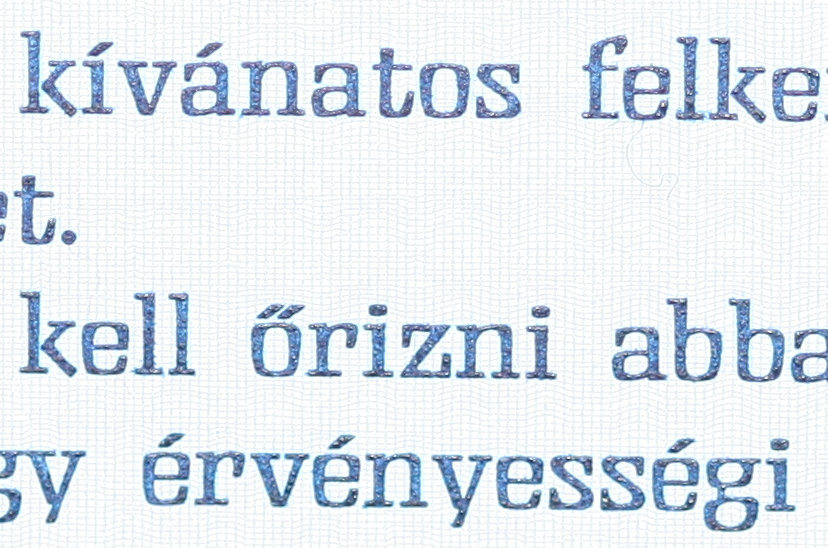
Ich hatte wegen des Hungarumlaut-Problems mal einen Bug-Report eingereicht – und Bruno Maag und Mark Shuttleworth haben beide geantwortet. Ich fühle mich ja so geehrt! :party:
Das Problem, dass die beiden kollidieren, wenn sie den selben, flachen Winkel haben wie der einfache acute, ist vermutlich jedem bekannt, der die Zeichen schon mal gezeichnet hat.
Man kann also ...
- den Winkel generell steiler machen (geht nicht mit jedem Entwurfsgedanke)
- Spezialversionen des acute für Ungarn erstellen, damit sie zum umlaut passen (mit den entsprechend auftauchenden technischen Hürden)
- ist es denn "erlaubt", den umlaut im selben Winkel, aber mit etwas kürzeren Strichen zu zeichnen? So könnte man eine Kollision beim engeren Zusammenrücken in manchen Fällen auch vermeiden.
ist es denn "erlaubt", den umlaut im selben Winkel, aber mit etwas kürzeren Strichen zu zeichnen?
Ich entscheide das natürlich nicht, aber im Prinzip würde ich erst mal sagen: nein. Der Grundsatz, so wie ich ihn verstehe, ist:
• Kurze Vokale haben keinen, einen oder zwei Punkte (a, i, ö). (Statt Punkten sind die normal üblichen Alternativformen akzeptabel, z.B. Quadrate.)
• Bei langen Vokalen wird jeder Punkt (bzw. jedes Quadrat) durch einen Strich ersetzt (andere Formen, z.B. Dreiecke, sind auch OK, aber selten). Also: ein Punkt -> ein Strich (i -> í), zwei Punkte -> zwei Striche (ö -> ő).
• Kurze Vokale ohne Punkt (a, e, o, u) werden so behandelt, als hätten sie einen.
Man hat also immer diese Beziehung: Punkt(e)=kurzer Vokal; Strich(e)=langer Vokal.
Unterschiedliche Strichformen bei ó und ő dürften Lesern ungarischer Texte also etwa genauso »falsch« vorkommen wie Lesern deutscher Texte unterschiedliche Punktformen bei i und ä (sagen wir mal: ein normaler i-Punkt mit Quadraten über den Umlauten).
Diesem Einheitlichkeitsprinzip werden andere Erwägungen anscheinend kompromisslos untergeordnet. Hast du den Text in ungarischen Pässen mal angesehen (das war das klarste Beispiel eines höchstoffiziell für angemessen befundenen Schrift, die ich auf die Schnelle finden konnte)?
Da sind die Striche nicht allzu steil, die Strichform beim ő wurde aber trotzdem nicht verändert. Dass das bei kleinen Schriftgraden dann zusammen läuft und nur noch wie ein Parallelogramm aussieht, ist offensichtlich das kleinere Übel. (Ich habe die Passseite mit einem Makroobjektiv fotografiert; tatsächlich ist die Schrift klitzeklein und die Striche des ő sind nur mit Mühe als solche zu erkennen.)
Ich habe auch schon extremere Beispiele mit noch flacheren Strichen gesehen, bei denen das Prinzip aber auch beachtet wurde.
Danke – das heißt dann wohl Feintuning bzw. Balance-Akt in der Schriftgestaltung ...
Wenn du Beispiele/Entwürfe hast, kannst du sie ja mal zeigen und ich frage dann mal die ungarischen Muttersprachler in meinem Umkreis, ob das so geht.
Sicherlich müssen der Akut und der halbe Doppelakut nicht exakt identisch sein, sie sollen nur optisch so wirken (wenn man nicht gerade mit der Lupe kuckt). Diese Beispiele von Linux- und Windows-Systemschriften (bin gerade unterwegs und habe keinen Mac) liegen wohl alle im Rahmen – eben bis auf die Ubuntu, die klar heraus fällt.